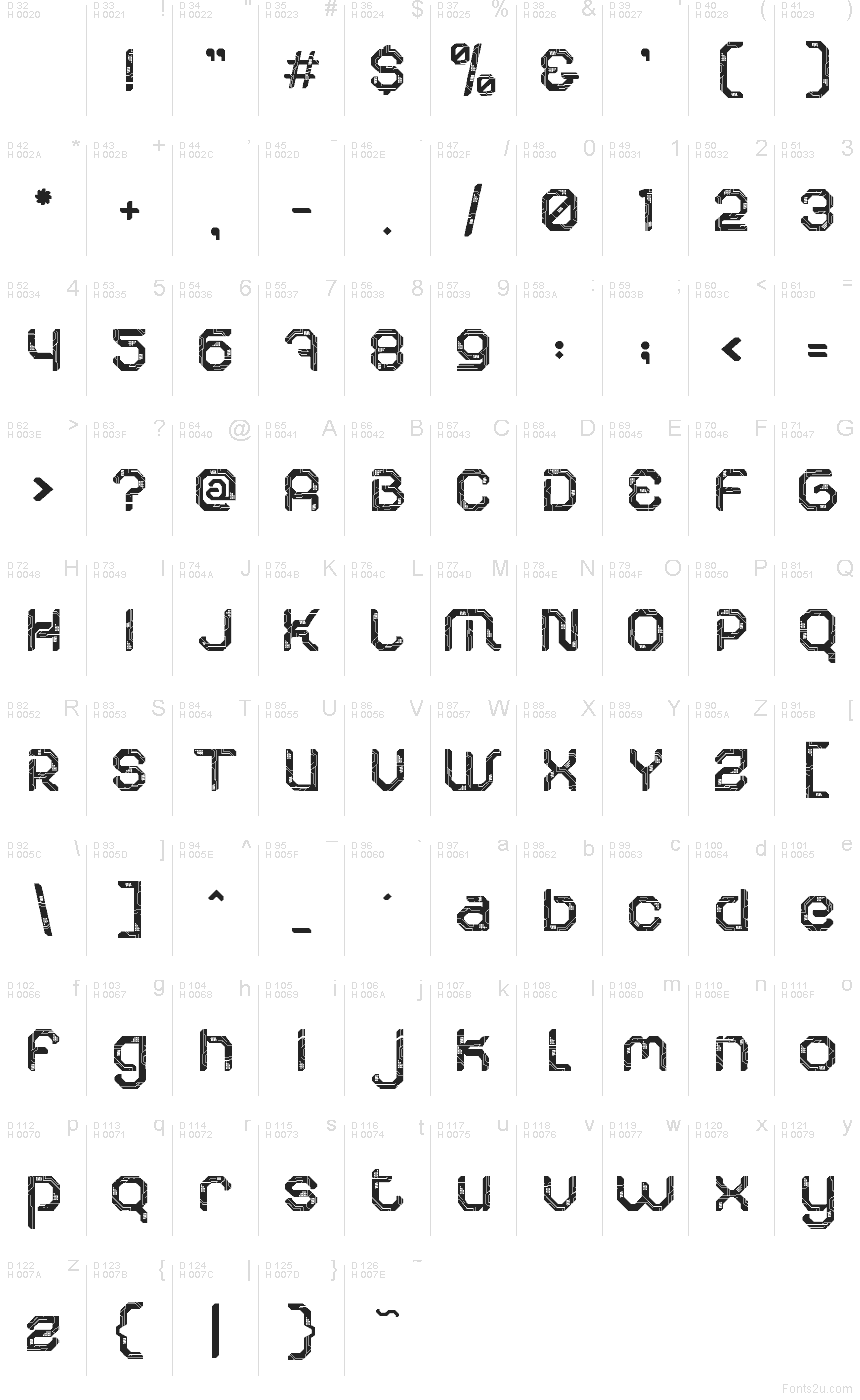
Snapshock Four
Snapshock Four od Putracetol Studio je futuristické písmo typu display inšpirované dizajnom plošných spojov. Vďaka skoseným hranám, vrytým líniám a malým mriežkovým blokom, ktoré sa opakujú v znakoch, získava tento font technickú textúru, ktorá pôsobí skôr ako ovládacie rozhranie zo sci-fi filmu než ako bežné geometrické písmo.
Toto segmentované detailné spracovanie je ako stvorené pre názvy hier, e-športovú grafiku, technologické plagáty, obaly albumov či streamovacie overlaye, kde sa vyžaduje silná digitálna identita. Písmo tiež dodá moderný šmrnc obalom produktov či vizuálom na sociálne siete pre gadgety a tvorbu v štýle synthwave, najmä pri krátkych slovách, kde najlepšie vynikne jeho integrovaná štruktúra obvodov.